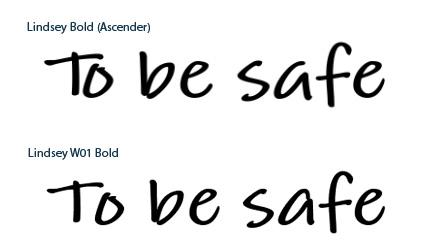
Lindsey Bold – zwei Varianten
bei dem Versuch, eine Schrift zu identifizieren, bin ich bei der Lindsey Bold von Ascender gelandet. Kurioserweise sind mir zwei leicht unterschiedliche Varianten untergekommen, wobei ich die zweite („Lindsey W01 Bold“) nur auf fragwürdigen Websites und ohne Angabe des Anbieters gesehen habe.
Kann es sein, dass jemand den Original-Font leicht modifiziert hat, um Probleme mit dem Urheberrecht zu vermeiden? Oder war W01 eine frühe Variante?